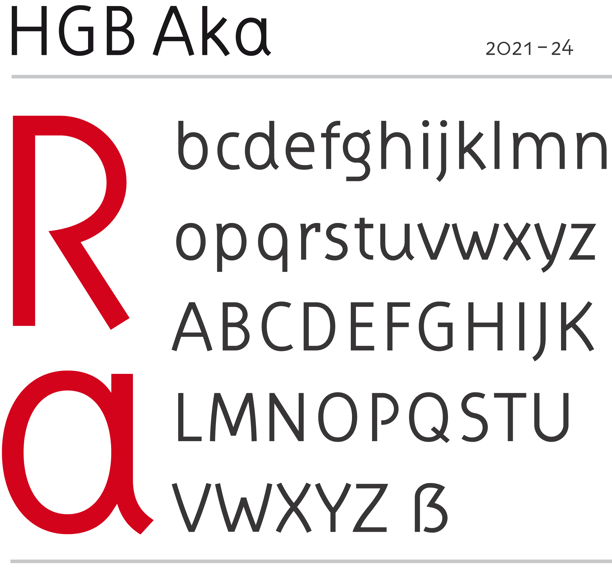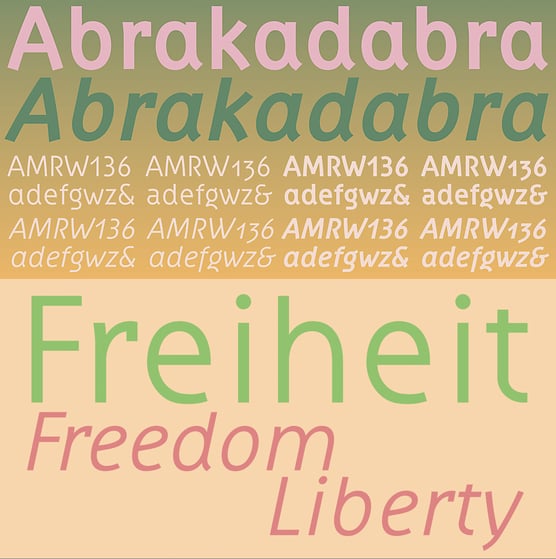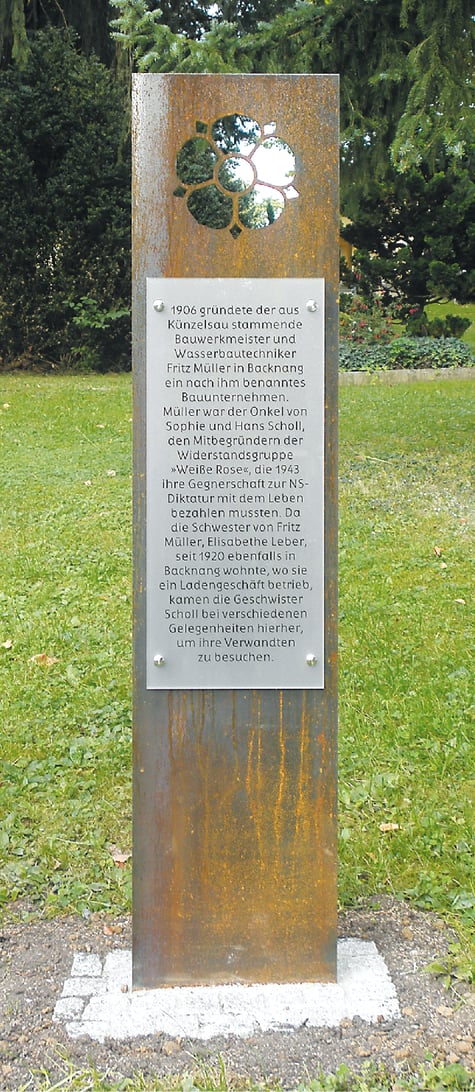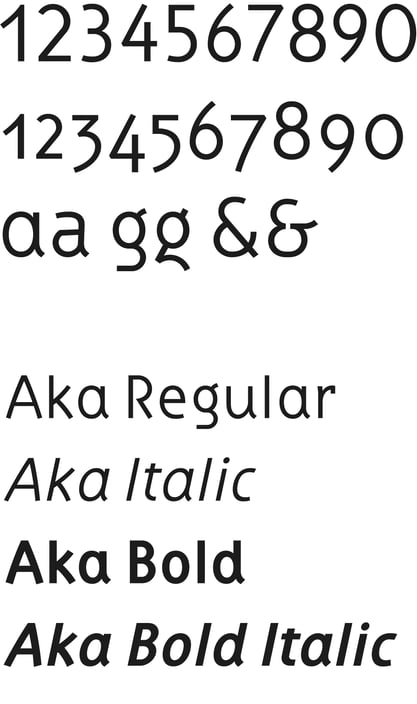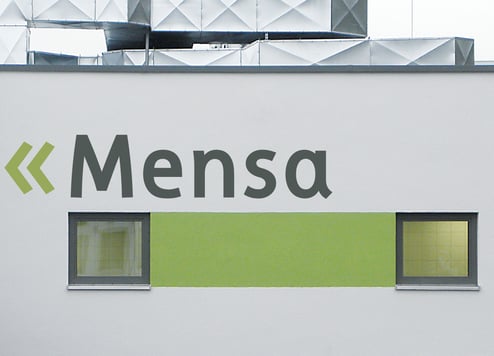
HGB Aka
HGB Aka ist angeregt durch ein Schriftprojekt von Günter Jacki für den Deutschen Werkbund. Günter Jacki war mein Lehrer in der Schriftklasse der Kunstakademie und ich durfte ihm jetzt, nach 50 Jahren, beim Einstieg in die digitale Schriftherstellung behilflich sein. Dem Zeitgeist der 1920er Jahre, als in Stuttgart die Weißenhofsiedlung entstand, soll hier nachgespürt werden. Es gab zu jener Zeit nicht nur in der Architektur moderne Tendenzen. Nach dem gemeinsamen Einstieg in das Projekt blieben hier einige Buchstaben übrig, an denen ich noch eine Weile herumprobiert habe. Als auf dem Backnanger Stadtfriedhof eine Erinnerungstafel zum 100. Geburtstag von Sophie Scholl geplant wurde, kam dieses Formprinzip gerade recht. Der Grabstein von Fritz Müller, einem Onkel der Geschwister Scholl, ist erhalten und als Schrift für die Gedenktafel habe ich den Schriftentwurf vervollständigt und ausgefeilt. Jetzt passt die Schrift gut zur Beschriftung des Grabsteins aus den 1920er-Jahren und ist auf die Entfernung leicht zu lesen. Der Text ist auf eine Cortenstahlplatte montiert, aus der eine Rose ausgelasert ist.